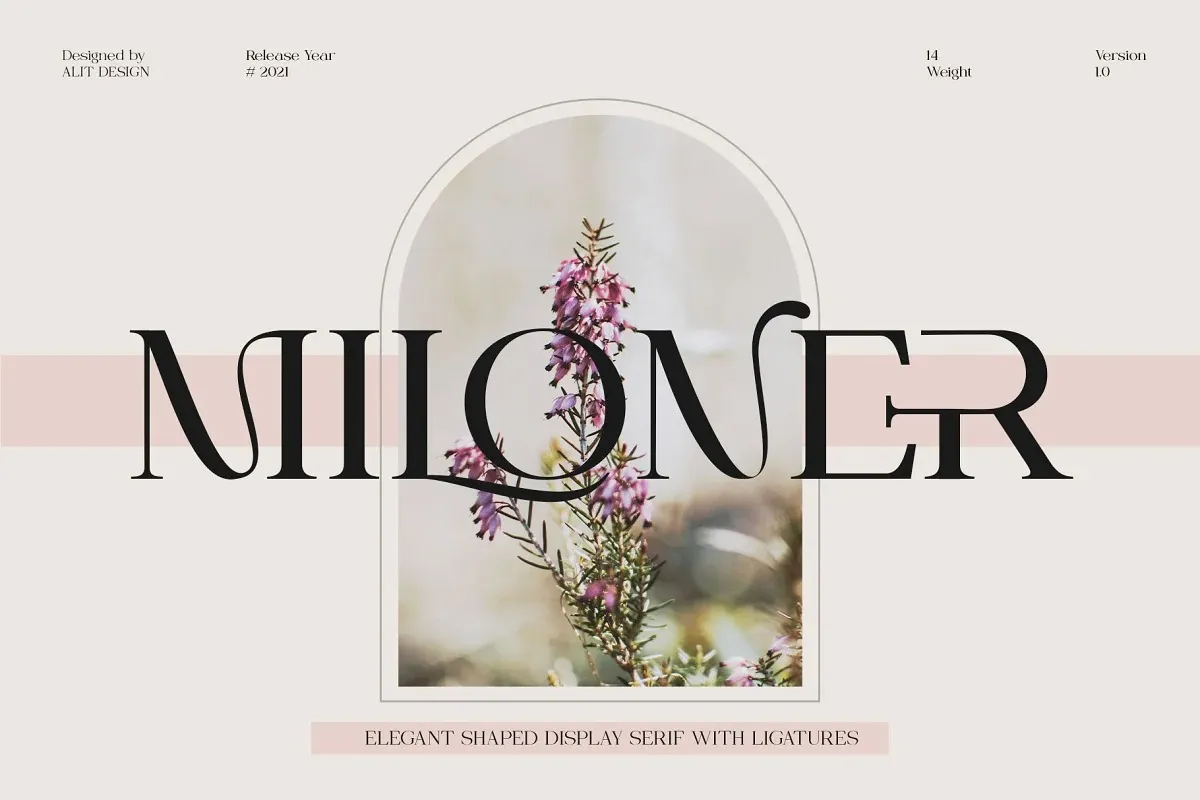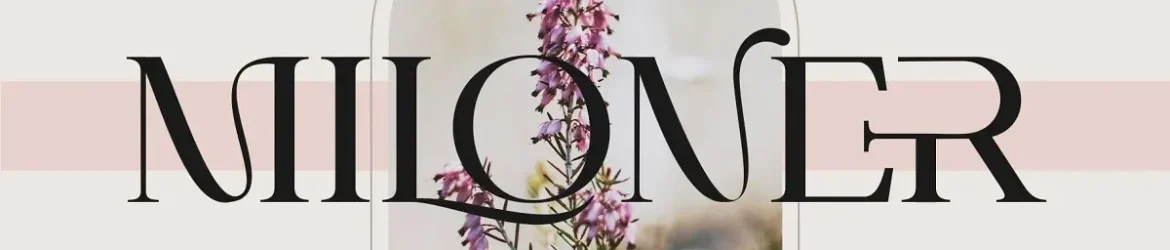
A Miloner é uma elegante fonte serif criada por alit design com curvas equilibradas, perfeitamente adaptada para designers que procuram uma opção sofisticada e moderna. Esta fonte serifa possui 14 familiações variando de Thin até Heavy, cada uma com seu próprio toque único. O design da Miloner não apenas captura a atenção dos destinatários do público-alvo de projetos gráficos, mas também traz um charme refinado e luxuoso ao trabalho. Seja para criar elementos chamativos ou tornar designs tradicionais mais sofisticados, a Miloner promete fazer sua marca com estilo único. Ideal tanto para designers digitais quanto para profissionais de design gráfico tradicional, esta fonte é perfeita para aqueles que valorizam um toque moderno e elegante em seus projetos.